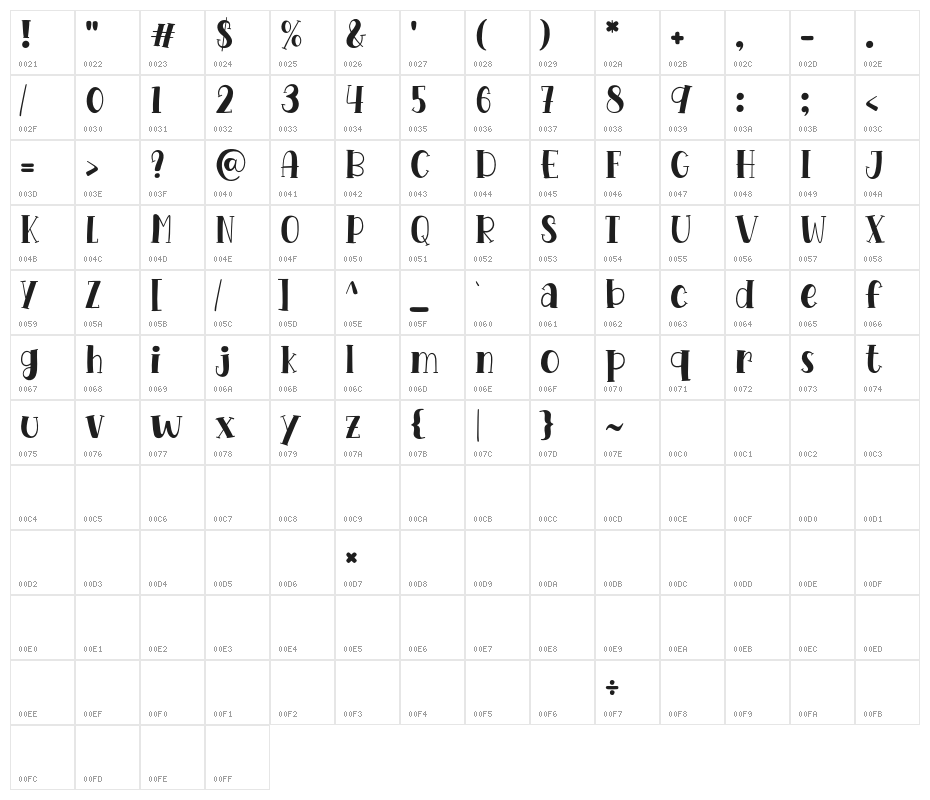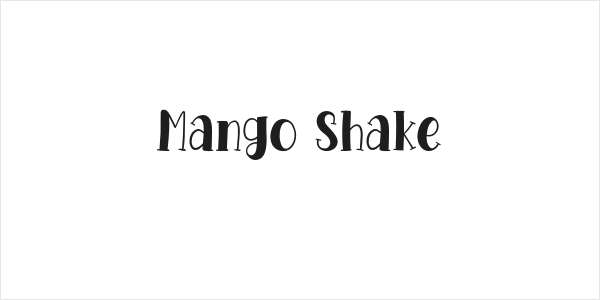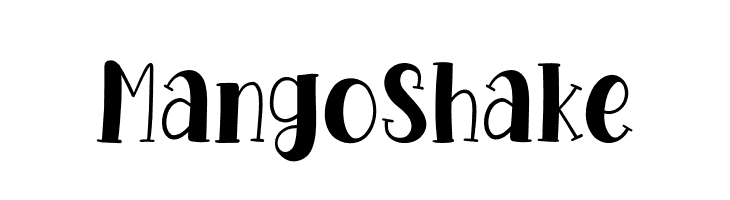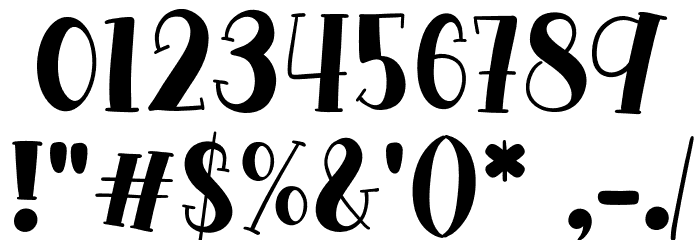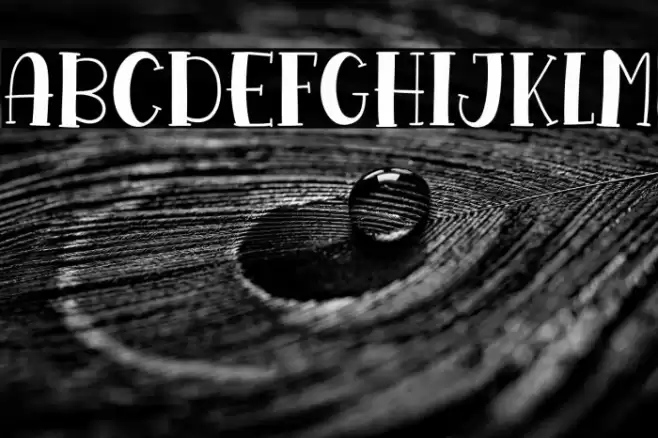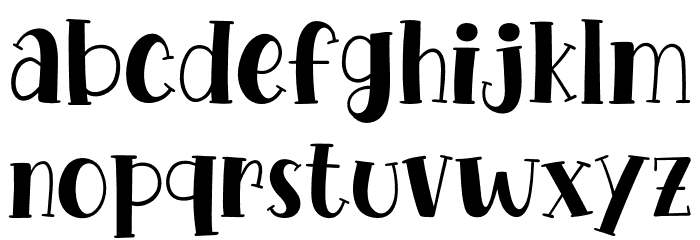
Mango Shake Font
| Stil general | Playful, Whimsical |
| Proiecte propuse | Ideal for children's books, playful branding, party invitations, and creative posters. |